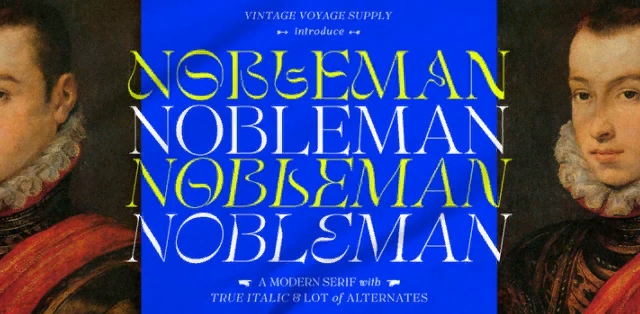
Название: VVS Nobleman Font (2021)
С гордостью представляем вам Nobleman - классическую засечку, наполненную современным настроением. Nobleman - это результат поиска базовой засечки с некоторыми интересными элементами, которые привносят этот стильный современный вид в вашу типографику. Высокий контраст между толстыми и тонкими штрихами придает Nobleman такой стильный вид. Nobleman имеет множество функций открытого типа, таких как чередование, лигатуры, дробь, старый стиль, табличные фигуры и малые прописные буквы. Nobleman имеет стиль True Italic и специальный стиль для небольших текстов, который имеет более мягкие контрастные штрихи, чтобы быть более читаемым.
Название: VVS Nobleman Font (2021)
С гордостью представляем вам Nobleman - классическую засечку, наполненную современным настроением. Nobleman - это результат поиска базовой засечки с некоторыми интересными элементами, которые привносят этот стильный современный вид в вашу типографику. Высокий контраст между толстыми и тонкими штрихами придает Nobleman такой стильный вид. Nobleman имеет множество функций открытого типа, таких как чередование, лигатуры, дробь, старый стиль, табличные фигуры и малые прописные буквы. Nobleman имеет стиль True Italic и специальный стиль для небольших текстов, который имеет более мягкие контрастные штрихи, чтобы быть более читаемым.